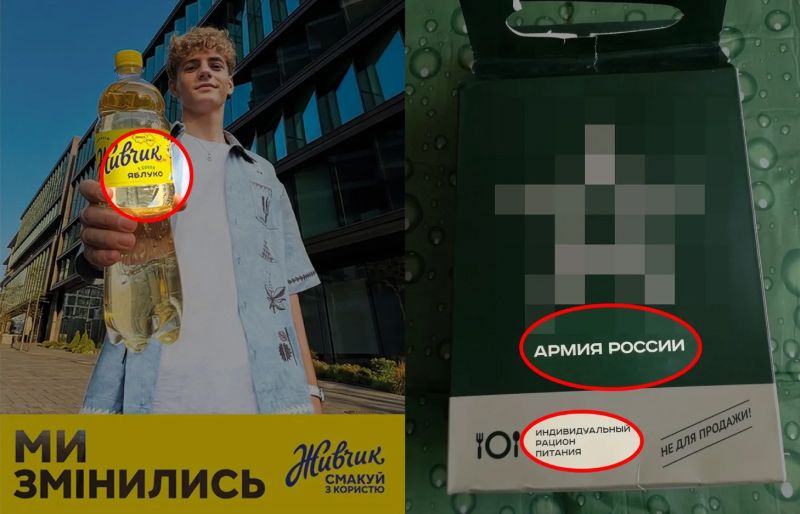
Новий "Живчик" у центрі скандалу: як відреагували розробники та що пропонують українцям
Після ребрендингу обговорення щодо нового "Живчика" не вщухають. Спочатку були меми й прохання повернути попередній дизайн, потім користувачі знайшли на етикетці нібито російський шрифт.
Чому виник скандал
Про те, що не так із новим "Живчиком", українці пишуть у Threаds.
Частина з коментарів стосується нової форми пляшки та етикетки, яка стала більш мінімалістичною.
Однак етикетку критикували не лише за це. Виявилося, що один зі шрифтів схожий на Road Radio, який розробила Elena Kowalski, дизайнерка російського походження, під псевдонімом Glen Jan.
Порівняння шрифту "Живчик" / Фото з соцмереж
Що запропонували розробники дизайну
Креативна агенція Brain Tank, яка працювала з новим дизайном етикетки "Живчика", відреагувала на критику. У Threads розробники написали, що не здогадувались про значення напою як національного символу.
До того ж фахівців здивувала "кількість емоційних та професійних коментарів, щодо дизайну нової етикетки".
Так, в агентстві оголосили грант. Користувачі можуть запропонувати свій редизайн і виправити все, що не сподобалося у варіації розробників. Далі якщо дизайн набере більше, ніж 25 0001 вподобайку – компанія виплатить премію в 50 002 гривні (після оподаткування).
Водночас щодо нібито російського шрифту в агенції наголосили:
Вкрай важливішим є сенситивне питання шрифтової гарнітури, яке ми зараз ретельно пропрацьовуємо та вийдемо невдовзі із рішенням,
– йдеться в повідомленні.
Нагадаємо, 29 травня бренд "Живчик" оголосив про ребрендинг. Компанія пов'язала зміни з дорослішанням і зазначила, що легендарний напій "виріс та змінився".
Реакція користувачів була різною, але позитивних відгуків найменше. Більшість коментарів у соцмережах була однотипною – зі зверненням до компанії повернути попередній дизайн.